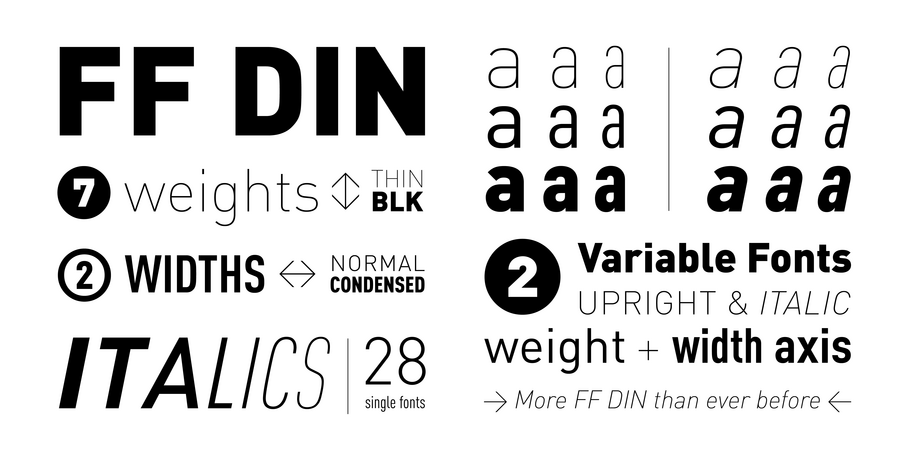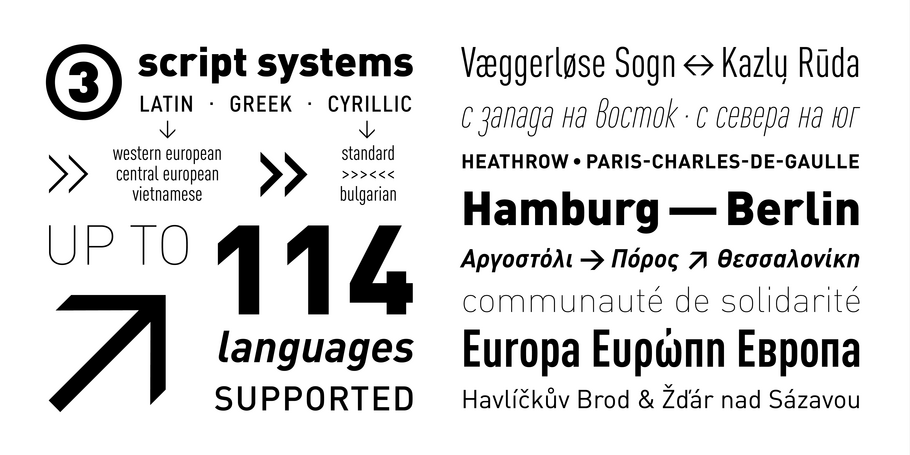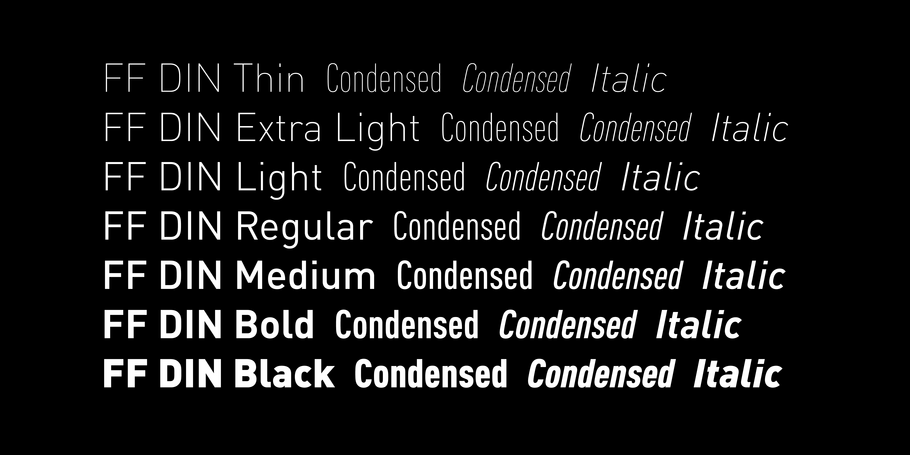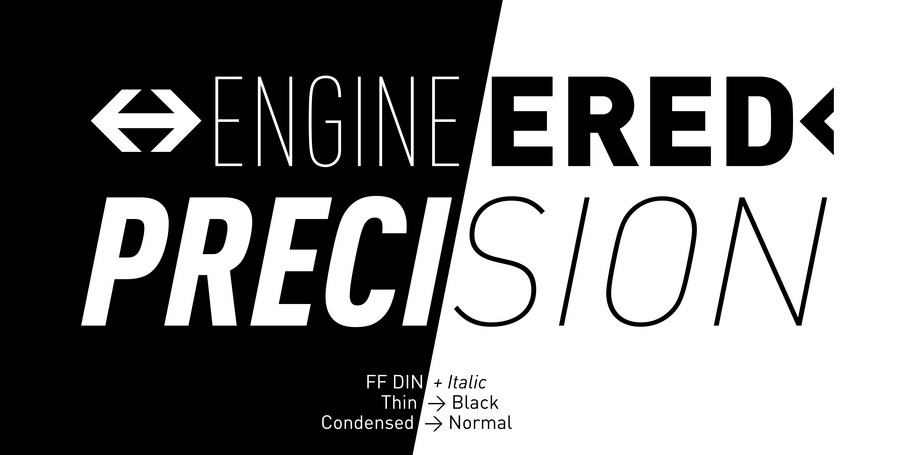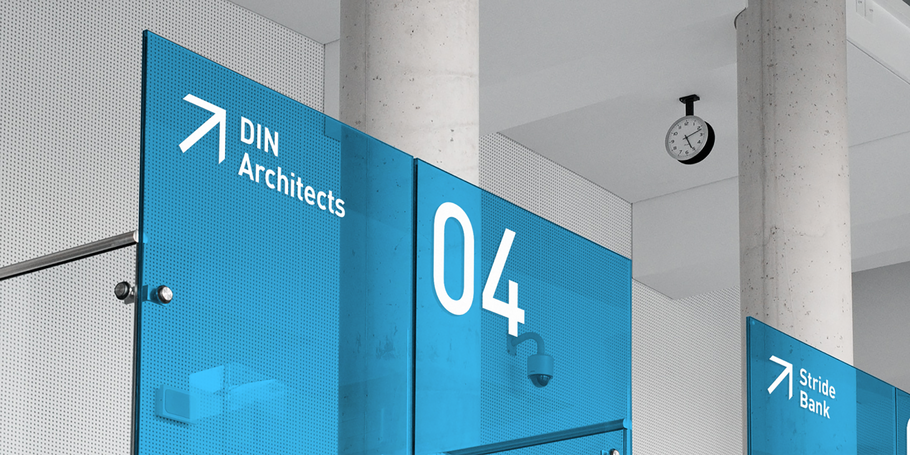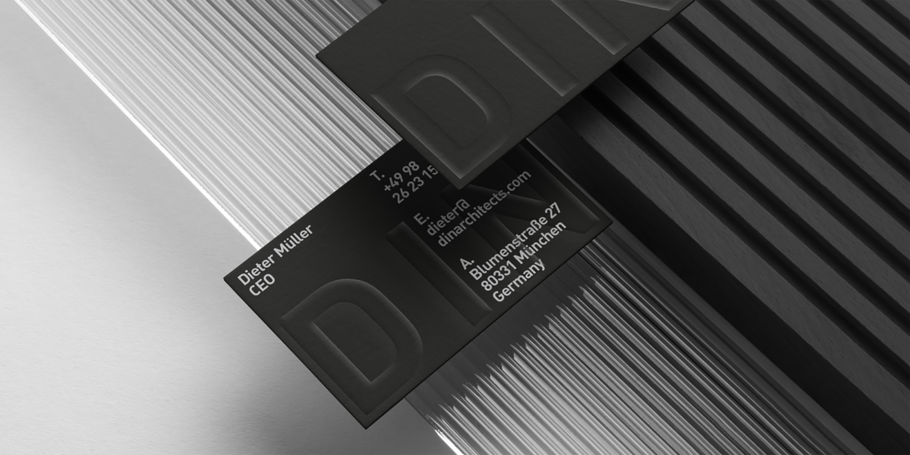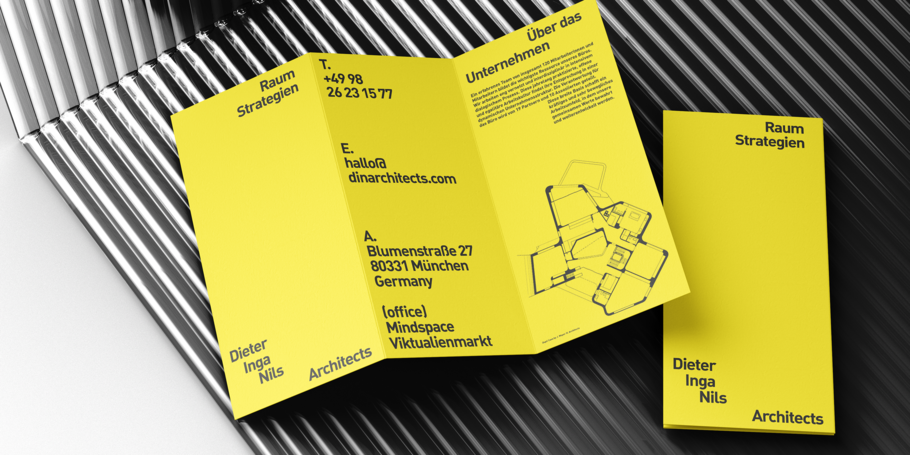
FF DIN Variable
Plus de FF DIN que jamais.
Précision, voilà le mantra de FF DIN. FF DIN Variable ne fait pas exception à l’expression de cette philosophie du design. FF DIN Variable vous offre encore plus de FF DIN que jamais. Repoussant les limites de la technologie des fontes, les fontes variables apportent aux créatifs un outil pour composer des variations particulièrement spécifiques, capables de s’adapter à chaque espace de conception.
FF DIN : un premier renouveau fidèle de la célèbre DIN 1451. FF DIN est issue de la famille de caractères DIN 1451, modèle défini par l’Institut allemand de normalisation en 1931. Elle est considérée par nature comme la parfaite fontes standard, grâce à son design méthodique et architecturé.
FF DIN Variable vous offre encore plus de FF DIN que jamais. Repoussant les limites de la technologie des fontes, les fontes variables apportent aux créatifs un outil pour composer des variations particulièrement spécifiques, capables de s’adapter à chaque espace de conception. FF DIN Variable représente une avancée technique audacieuse, qui fusionne l’aspect technique de FF DIN avec la fluidité presque organique du monde des fontes variables.
Disponible dans les styles droit et italique, il y a beaucoup plus à découvrir de FF DIN avec cette nouvelle ère de la technologie typographique. FF DIN Italic est un style romain incliné, néanmoins optiquement corrigé – légèrement plus fin et plus étroit. FF DIN Italic sait donc se distinguer avec subtilité.
FF DIN Variable reste fidèle à l’ADN du design d’origine. Le plus grand soin a été apporté pour s’assurer que les nouvelles propositions de FF DIN Variable restent cohérentes avec l’ensemble des graisses appréciées de tous. Précision, voilà le mantra de FF DIN. FF DIN Variable ne fait pas exception à l’expression de cette philosophie du design. Produisez une typographie d’une finesse exquise et déployez des titres animés expressifs pour n’importe quel design.
Des styles à l’infini, intelligents et puissants.
Albert-Jan Pool est né à Amsterdam le 9 juillet 1960. Après des études à l’Académie royale des beaux-arts (KABK) de La Haye avec Gerrit Noordzij, il s’installe à Hambourg et travaille avec Scangraphic et URW. Depuis 1994, il dirige son studio Dutch Design et conçoit des fontes telles que FF OCR-F et FF DIN, mais aussi des fontes pour des marques comme Jet/Conoco, C&A et HEM/Tamoil.
Antonia Cornelius est une designer allemande en typographie et communication. Elle est aussi conférencière, auteure et chercheuse avec un intérêt particulier pour la lisibilité et l’intelligibilité. Elle a étudié le design de communication, et notamment le design typographique, avec Jovica Veljović à l’Université des sciences appliquées (HAW) de Hambourg. Juste après l’obtention de son master, Antonia a rejoint Dutch Design pour la création des extensions FF DIN Variable, Slab et Stencil.
Achaz Reuss a travaillé chez URW en tant que designer typographique, puis a fondé sa propre agence de design Reuss Design en 1995, spécialisée en design et en typographie d’entreprise. Il a notamment créé la fontes de marque de NIVEA en 2000. Il a également contribué à la fonte FF DIN de Albert-Jan Pool.